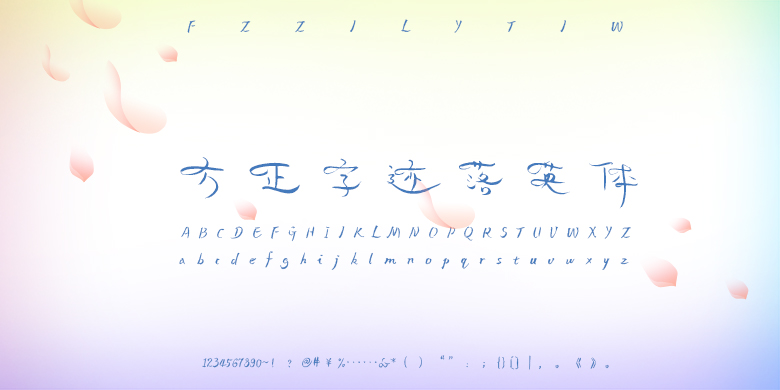
方正字迹-落英体
方正字迹-落英体,这款字体结构工整、笔画清晰,兼顾美观与易读性,适用于标题、正文、海报、包装、LOGO 等多种场景。字形优雅稳定,风格百搭耐看,适配日常排版与创意设计,让文字呈现更舒适、更具质感。方正字迹-落英体一笔一画,皆是细节,以均衡的比例、流畅的线条打造舒适视觉体验,字形端正大气,风格简约现代。无论是商业设计、品牌宣传还是日常排版,都能轻松驾驭,让文字更有格调与力量。方正字迹-落英体字体下载。
字体品牌: 方正字迹 设计师:夏薛阳 字体分类:创意书写 字体属性:精品字 字符集:大陆简体(GB2312-80)、简繁扩展(GBK) 发布时间: 2018
“芳草鲜美,落英缤纷”,每一个字都是一株生长的藤蔓。每一笔延伸的笔画,都是一支窈窕的枝丫;每一处转弯的圈圆,都是一片飘落的花瓣。作者夏薛阳的设计灵感来源于隶书,又融入了个人的书写风格,一步步从随手记的字体发展至今。给人传递一种惬意、自如而又美好的感觉。